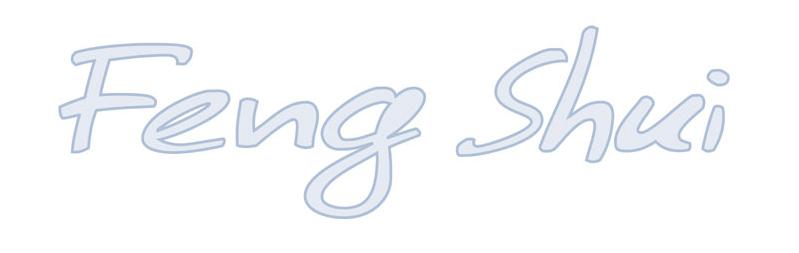
Outline und kursiv (Feng Shui)
Vor ca. 10 Jahren hat mein damaliger Grafiker eine Visitenkarte erstellt.
Diese enthält den Schriftzug Feng Shui.
Leider erinnert er sich nur noch, dass es eine freie Mac-Schrift ist.